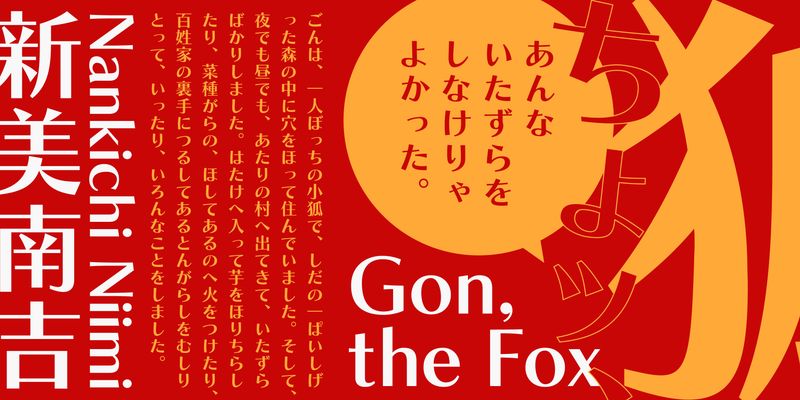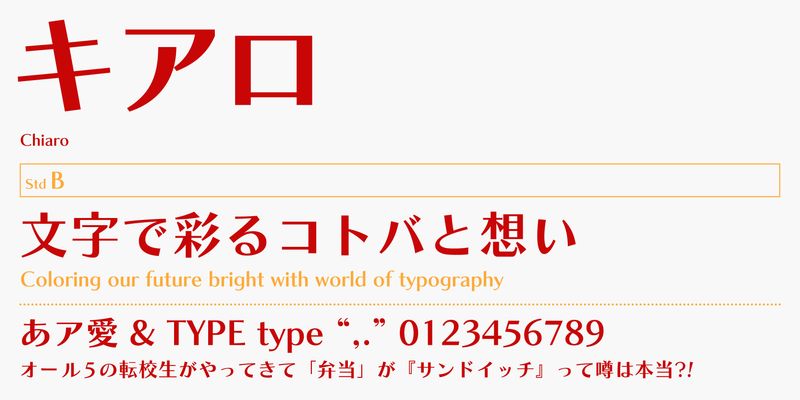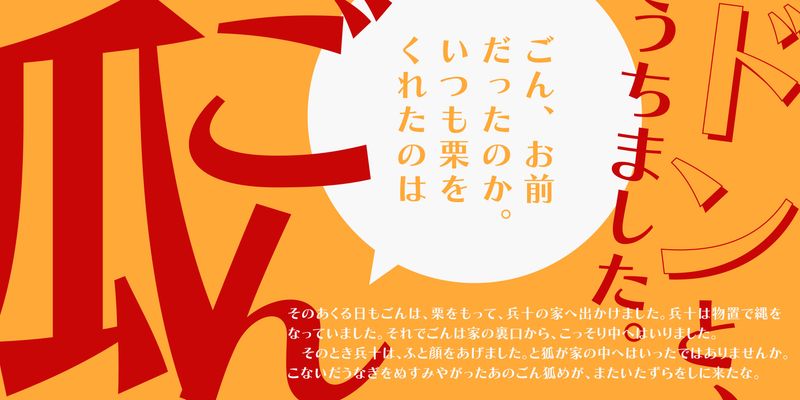
Die rhythmische Vermischung von Mincho und gotischen Stilelementen in dieser Schrift erzeugt ein scharfes und erfrischendes Bild. Der einzigartige Kontrasteffekt entsteht durch die Kombination der Strichführung im Mincho-Stil mit dem Anfang und dem Ende jedes Strichs im gotischen Stil.